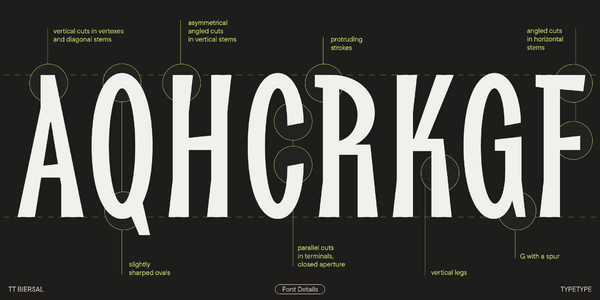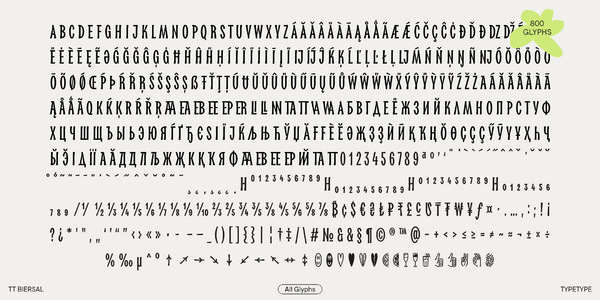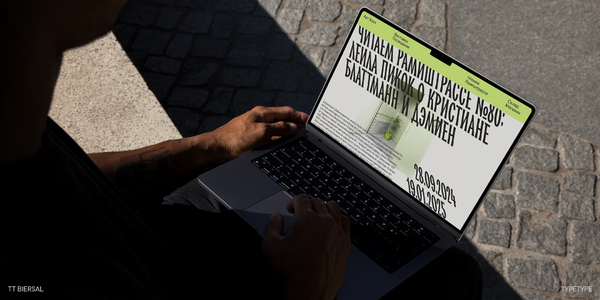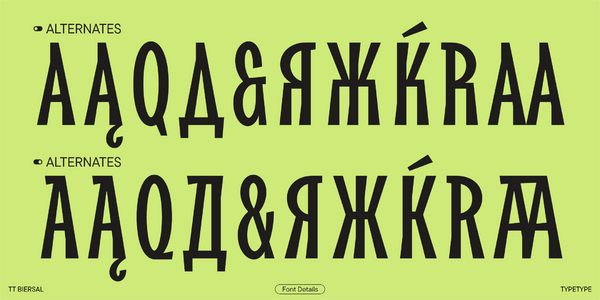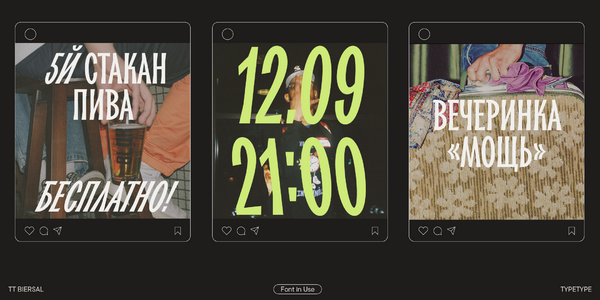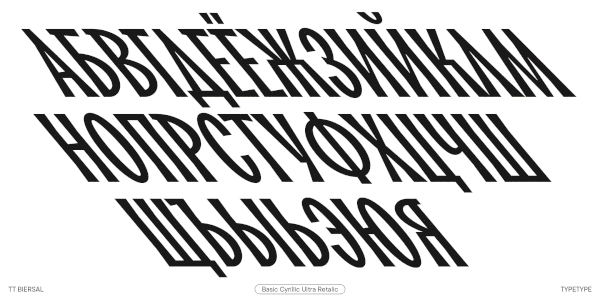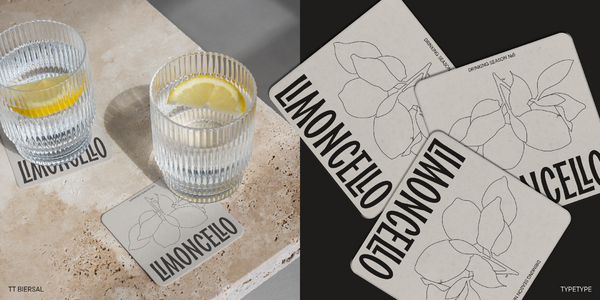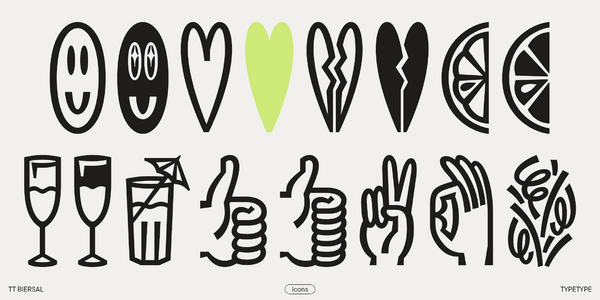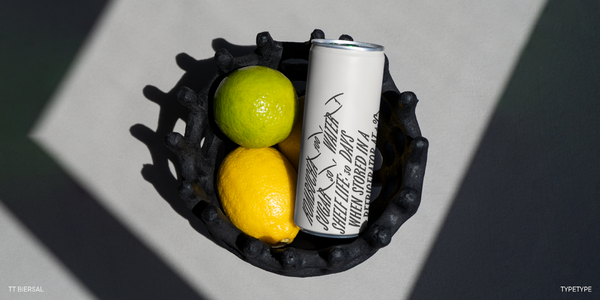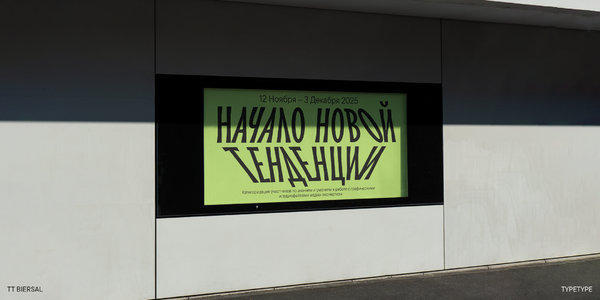
TT Biersal — ТТ Бьерсал
Произносится «ТТ Бьерсал». «Biersal» образовано от немецкого Bieresel — имени домашнего духа из мифологии. Буквы «TT» являются аббревиатурой названия компании.
TT Biersal — акцидентный гротеск со свободным, озорным и авантюрным характером. Его важная особенность — экстремальный наклон в реталиках и италиках.
TT Biersal — гуттаперчевый акцидентный гротеск
В традиционных шрифтовых гарнитурах наклонные начертания несут вспомогательные функции: они используются для того, чтобы логически структурировать текстовые блоки. Мы решили, что в этом шрифте все будет наоборот, и довели наклонные начертания до максимально возможных значений. А в результате получили экстремально выразительный стиль! Прямое начертание гарнитуры TT Biersal ассоциируется с рукотворностью, сочетает в себе ассиметричные срезы в прямых знаках и острую форму овалов. Наклонные начертания отличаются экстремальным наклоном в италиках и реталиках: угол наклона — от −40 до +40 градусов. Это создает очень яркий стиль и задает сильную динамику для чтения. В вариативном шрифте вы получаете динамику по углу наклона в 80 градусов. Дополнительно в гарнитуре присутствует вариативный сет иконок на тему вечеринок и комплект лигатур неожиданных форм.
Семейство состоит из 6 начертаний: 1 прямого, 4 наклонных и 1 вариативного
Шрифт отлично подходит для оформления фестивалей, анимаций, а также дизайна упаковки и обложек
Встречайте новый акцидентный TT Biersal! Самобытный и энергичный шрифт, вдохновленный типографикой первой половины 20 века.
TT Biersal — акцидентный гротеск со свободным, озорным и авантюрным характером. Отправной точкой для его создания послужил немецкий плакат начала 30-х годов. Мы хотели сохранить не только пропорции, но и ощущение небрежности, живости леттеринга из референса. В результате у нас получился насыщенный и плотный шрифт с узкими пропорциями и ассиметричными формами.
Характерные детали TT Biersal — ассиметричные срезы под углом в прямых и треугольных знаках. Они придают шрифту ощущение рукотворности: будто кто-то вырезал отдельные кусочки из бумаги, стекла или камня и собрал из них модульный коллаж. Нестандартные параллельные срезы в терминалах круглых букв делают рисунок динамичным. В некоторых буквах, таких как «Е», «Р» и «В» можно увидеть небольшие выступы — как будто штрихи немного вышли за вертикальные стемы при беглом письме. А овалы немного заострены для созвучности с острыми углами в прямых знаках.
Благодаря угловатым срезам, ассиметричным диагоналям и плотному набору рисунок шрифта напоминает переплетение веток на фоне ясного голубого неба. В наклонных начертаниях TT Biersal становится еще стремительнее и динамичнее. Мы добавили экстремальный наклон в реталики и италики — от -40° до +40°. Если совмещать блоки текста с разным наклоном, можно создать эффект движения или тени. Дополнить дизайн поможет сет иконок на тему вечеринок.
TT Biersal отлично подойдет для оформления музыкальных фестивалей, выставок, киноафиш. Бойкий дух шрифта придаст смелости любому дизайну. А благодаря рукописному началу он хорошо дополнит айдентику брендов, специализирующихся на крафтовых продуктах и изделиях, созданных вручную.
• 6 начертаний: 1 прямое, 2 италика, 2 реталика и 1 вариативный шрифт, меняющийся по оси наклона;
TT Biersal — король шрифтовых вечеринок!